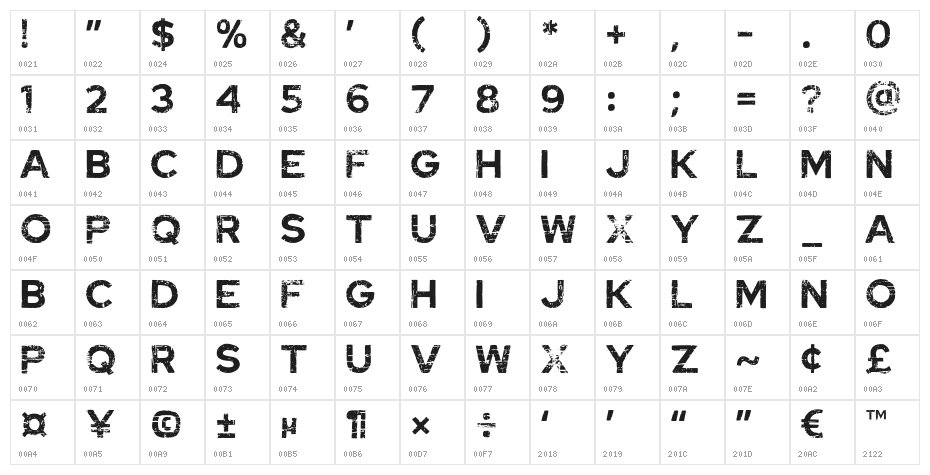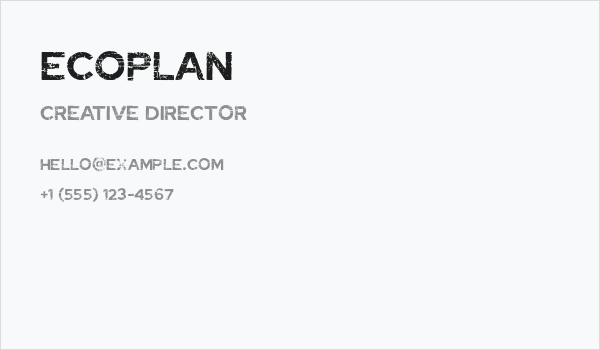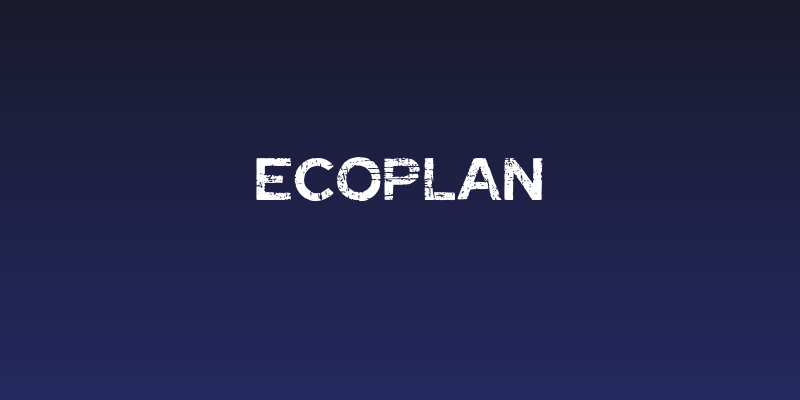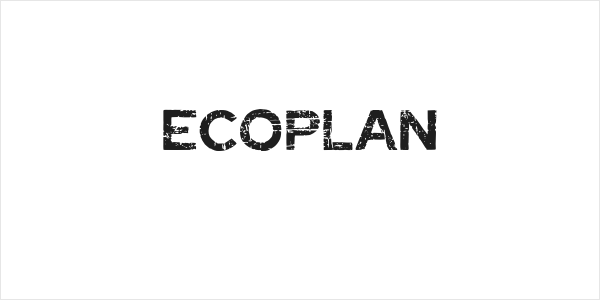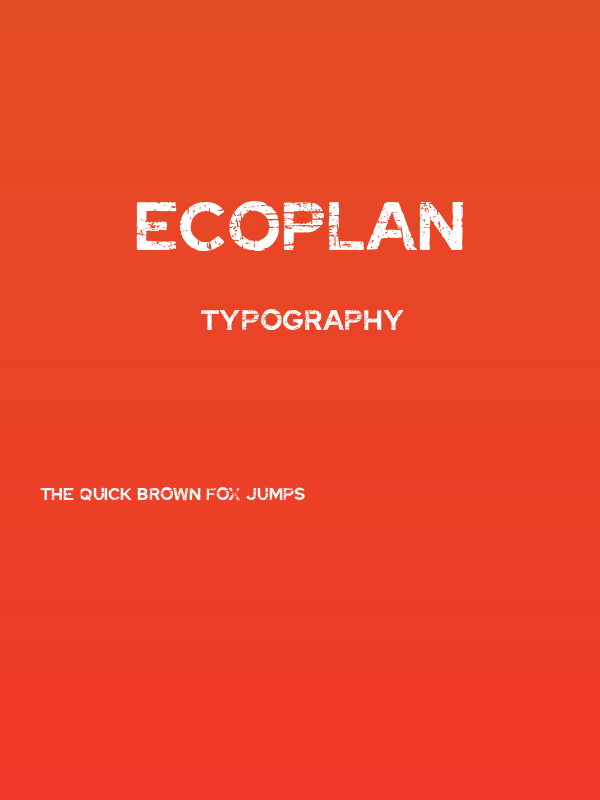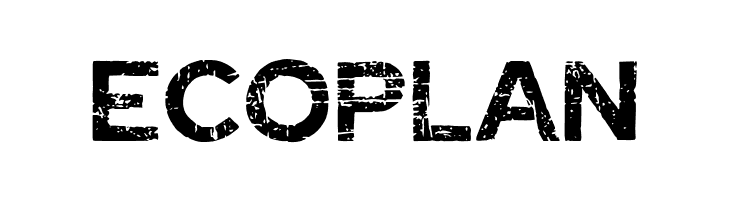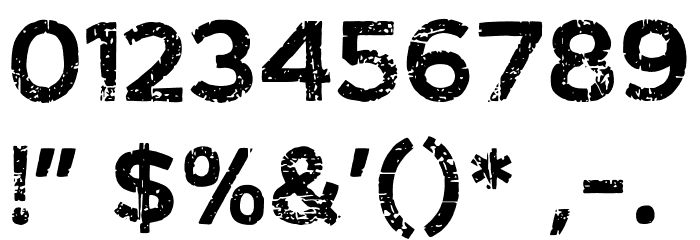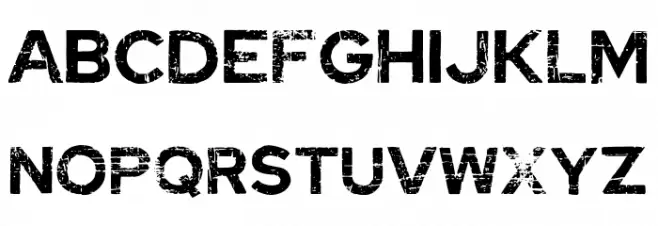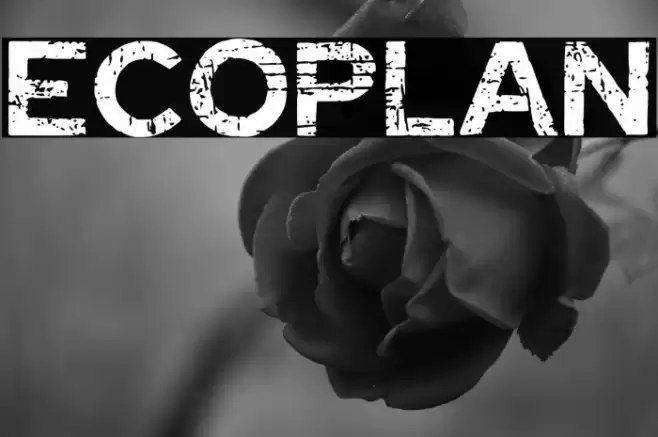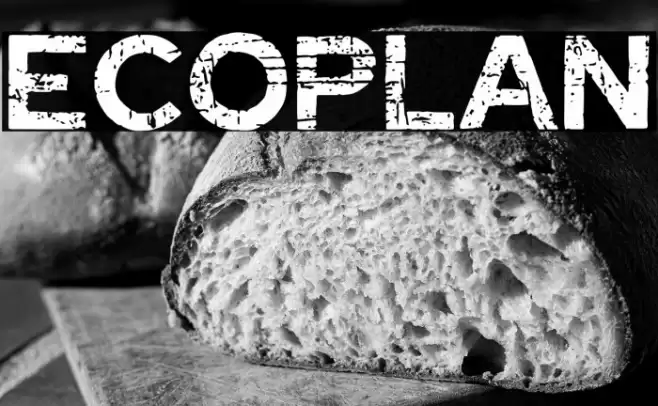
Ecoplan Font
Fonts by Khurasan
| Stil general | Grunge, Urban, Vintage |
| Proiecte propuse | Ideal for album covers, posters, branding for edgy or alternative products, and any design needing a gritty, urban feel. |
| Autor | Fonts by Khurasan |